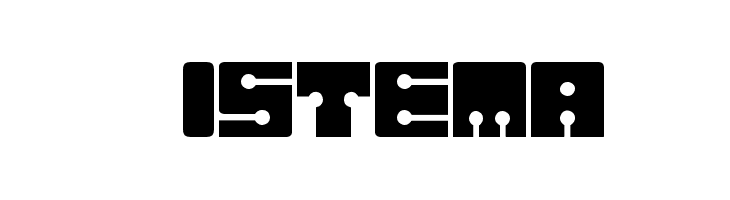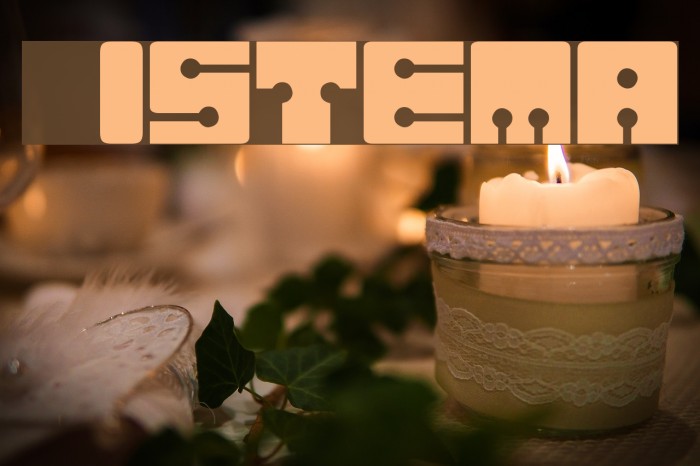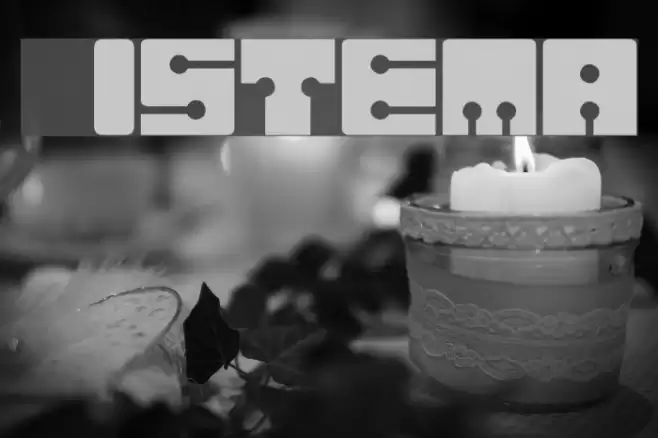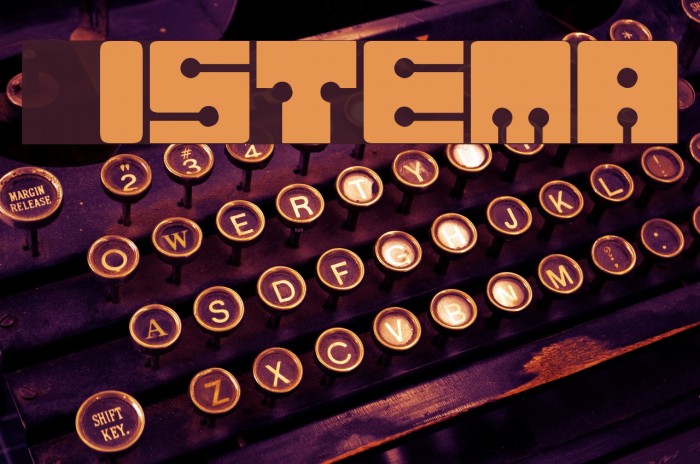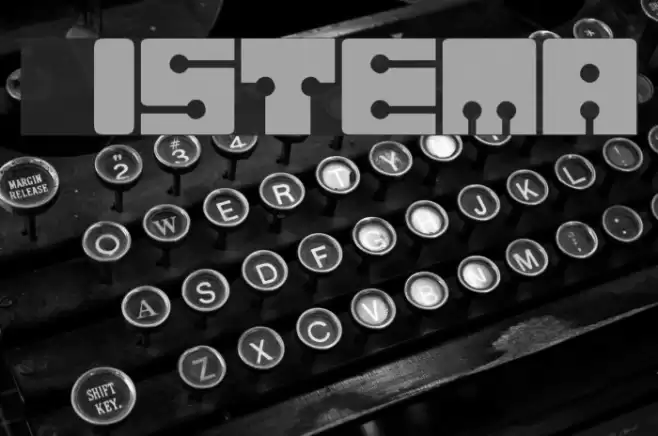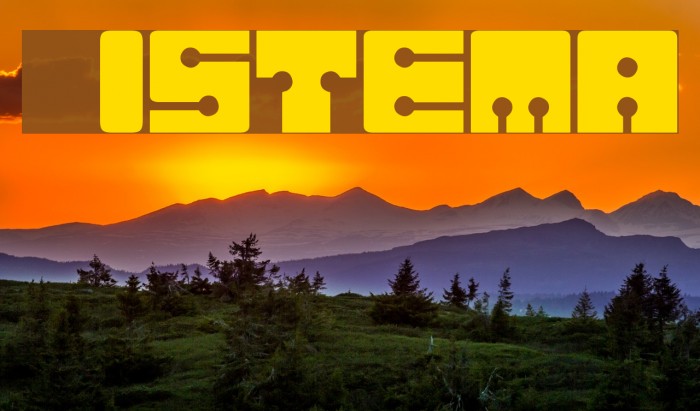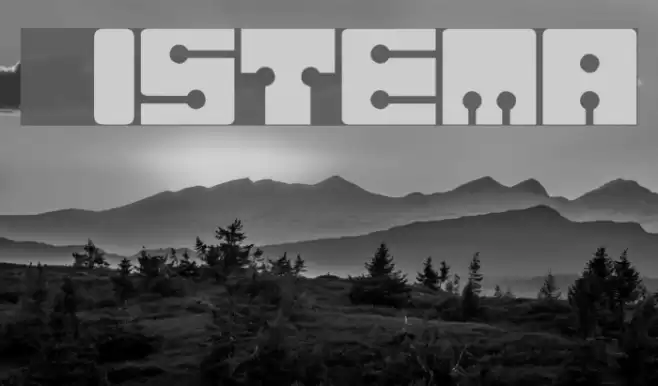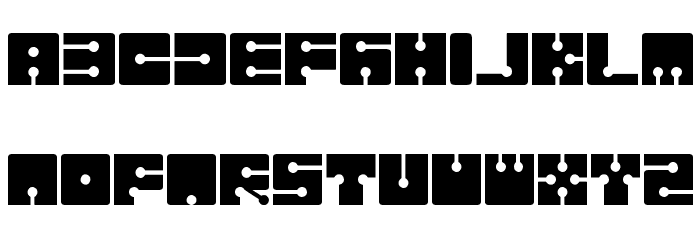
Sistema Font
| Estilo general | Futuristic, Modern |
| Caso de uso | Logos, Headlines, Posters |
| Proyectos propuestos | Ideal for technology branding, sci-fi themed posters, video game titles, and futuristic product packaging. |